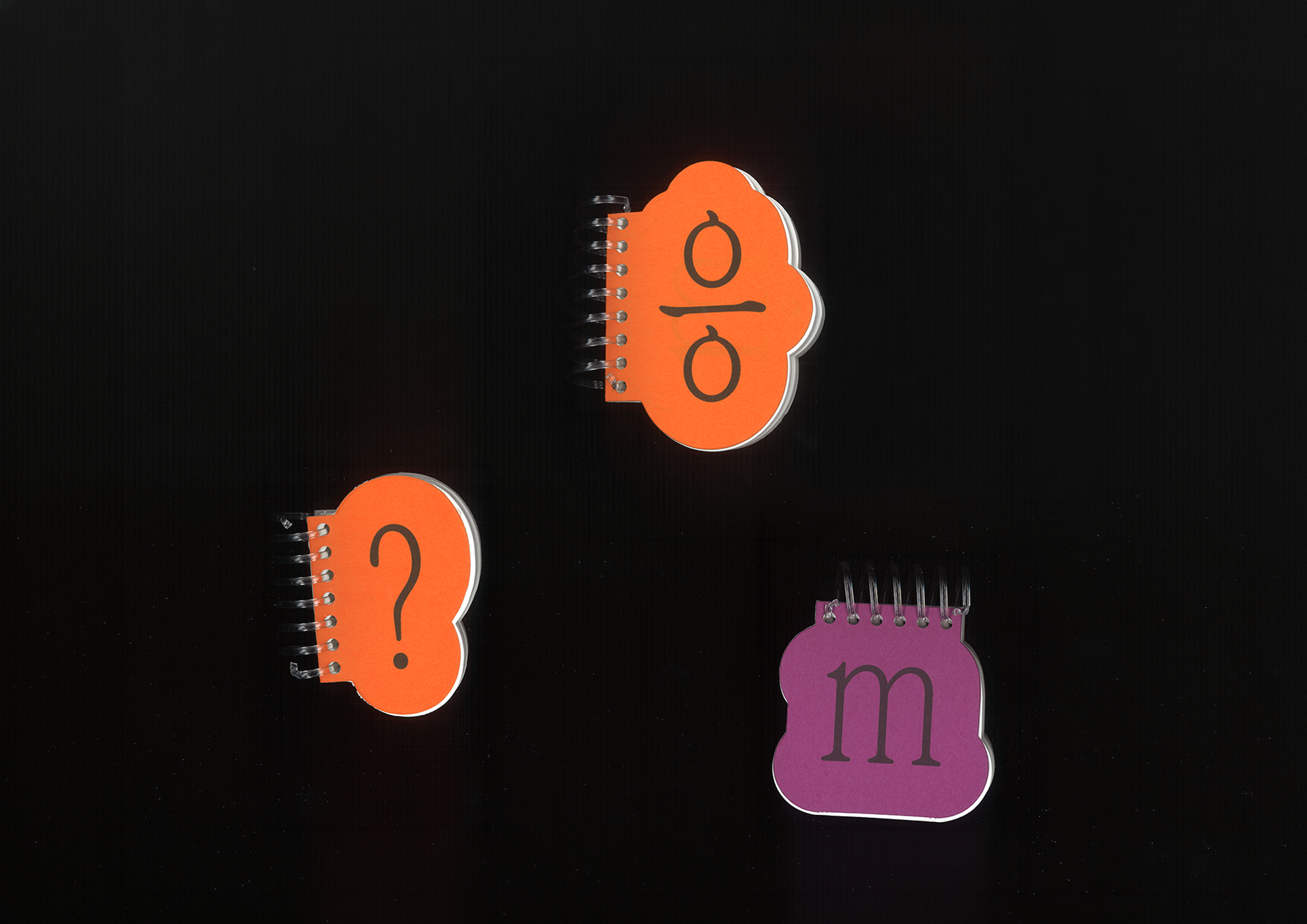
NU 시야 패밀리
NU Siya Family
«NU 시야»는 9:16 비율을 한글 폰트 조형 안으로 끌어들인 실험적인 본문용 폰트입니다. 한글 글립의 기본 단위인 1000UPM(Unit Per Em) 안에 9:16 비율을 단위화하여, 가로 562unit, 세로 1000unit의 좁고 높은 직사각형을 기준 그리드로 설정했습니다. 이러한 구조는 디지털 환경에서의 시각적 경험을 반영함과 동시에, 좁은 폭으로 더 많은 정보를 담아낼 수 있는 조형적 밀도를 형성합니다. 특히 세로형 판형과 스크롤 중심의 읽기 방식에서 텍스트가 더 많이, 빠르게 노출될 수 있는 장점을 갖습니다. 이처럼 «NU 시야»는 스크롤 시대의 감각과 정보 밀도의 변화를 타이포그래피 조형에 반영한 폰트입니다. Serif(6종), Sans(1종)로 구성되어 있으며, Sans의 웨이트는 2026년 5월에 추가될 예정입니다.